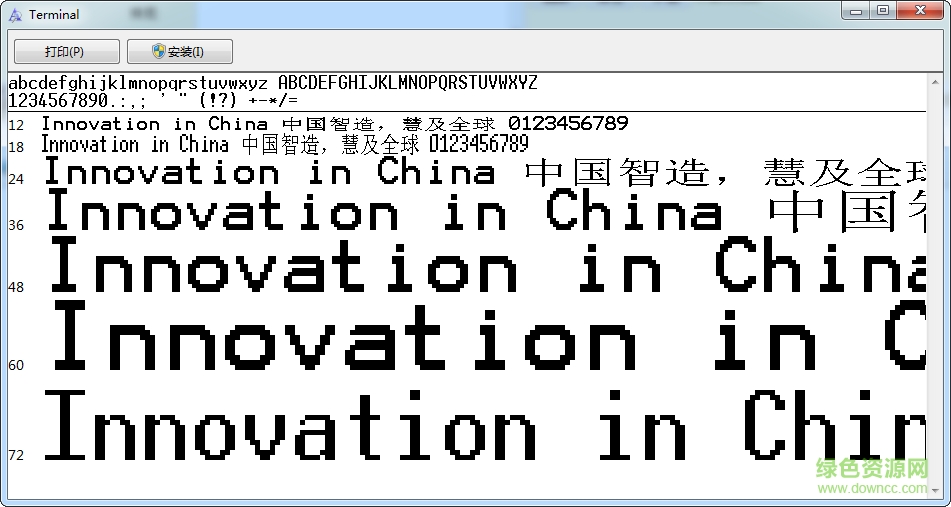
cga80woa.fon文件是一款win系統(tǒng)字體,這個(gè)字體使用是十分的廣泛,而且該字體會(huì)在很多情況下用到,而且這個(gè)字體文件十分的小巧輕便,會(huì)在較大的屏幕尺寸中替換,是一款非常不錯(cuò)的字體文件,喜歡就來(lái)綠色資源網(wǎng)下載吧!
矢量字體(。FON)
雖然擴(kuò)展名和光柵字體一樣,但是這種字體卻是由基于矢量的數(shù)學(xué)模型定義的,是Windows系統(tǒng)字體的一類,一些windows應(yīng)用程序會(huì)在較大尺寸的屏幕顯示中自動(dòng)使用矢量字體來(lái)代替光柵字體的顯示。
光柵字體(。FON)
這種字體是針對(duì)特定的顯示分辨率以不同大小存儲(chǔ)的位圖,用于Windows系統(tǒng)中屏幕上的菜單、按鈕等處文字的顯示。它并不是以矢量描述的,放大以后會(huì)出現(xiàn)鋸齒,只適合屏幕描述。不過(guò)它的顯示速度非???,所以作為系統(tǒng)字體而在Windows中使用。